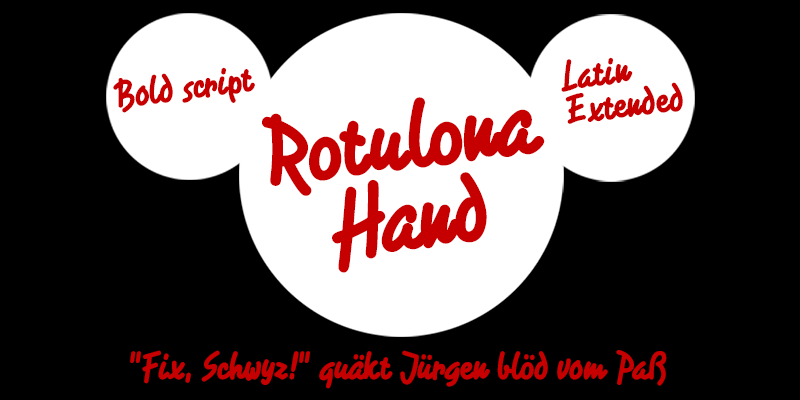
A Rotulona Hand é uma tipografia à mão escrita densa projetada com a ponta de tinta esférica rechoncunda de um canetão grosso. Este estilo descontraído e despreocupado está perfeitamente adaptado para design gráfico e propaganda. Suas linhas diretas e sua face jovial fazem dele uma opção ideal para criar designs alegres e eficazes. Esse fonte é ótimo para quem deseja adicionar um toque autêntico e quente em suas criações digitais, sem se preocupar com o peso de linhas finas. É livre de graça apenas para uso pessoal. Para adquirir uma licença comercial, por favor consulte Rotulona Hand. Com sua aparência confortável e fácil de digerir, a Rotulona Hand é perfeita para criar headlines chamativas ou destacar nomes de empresas em logotipos. Seja você um designer gráfico ou um criador digital, esta fonte vai tornar seu trabalho mais atraente sem precisar fazer grandes investimentos.